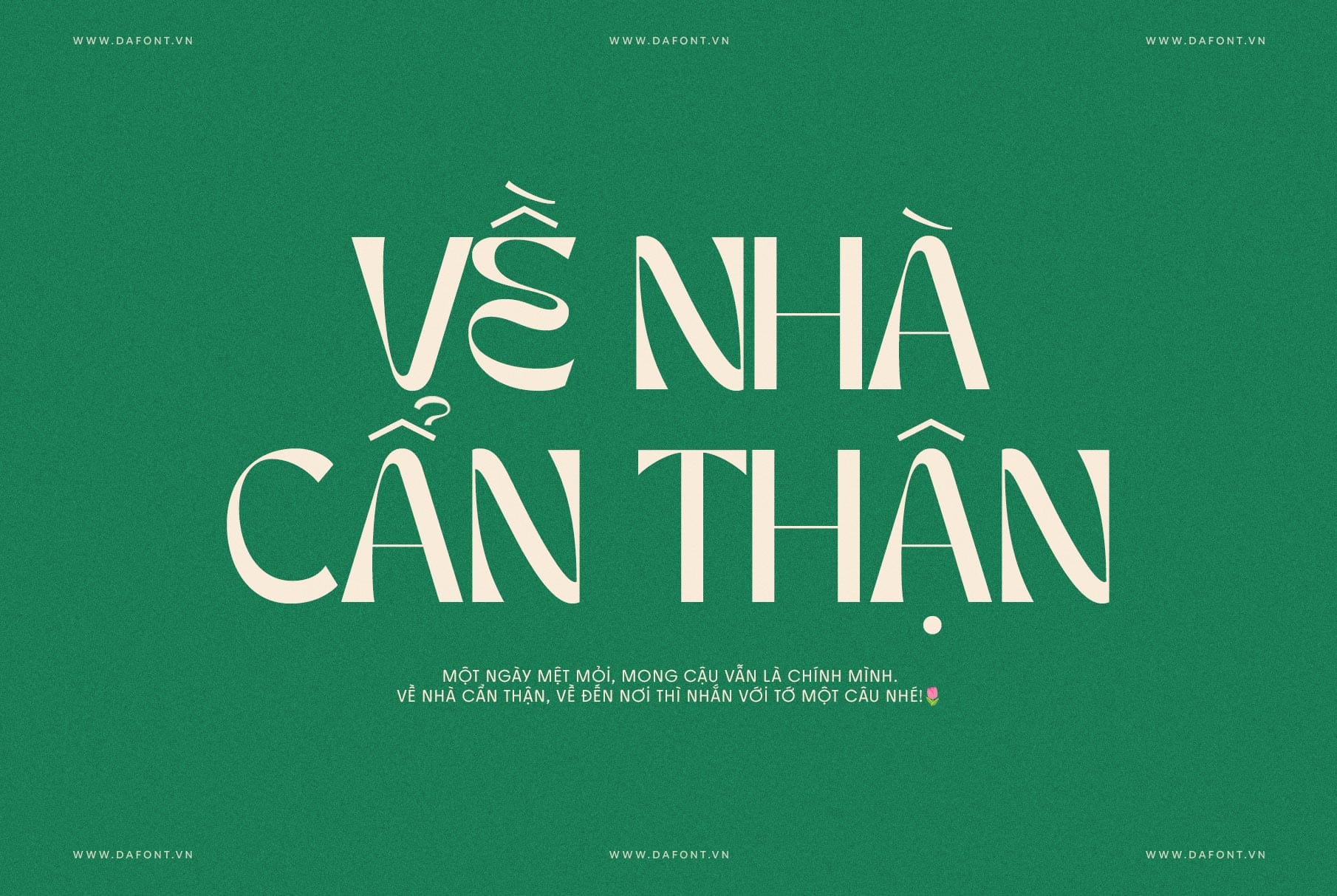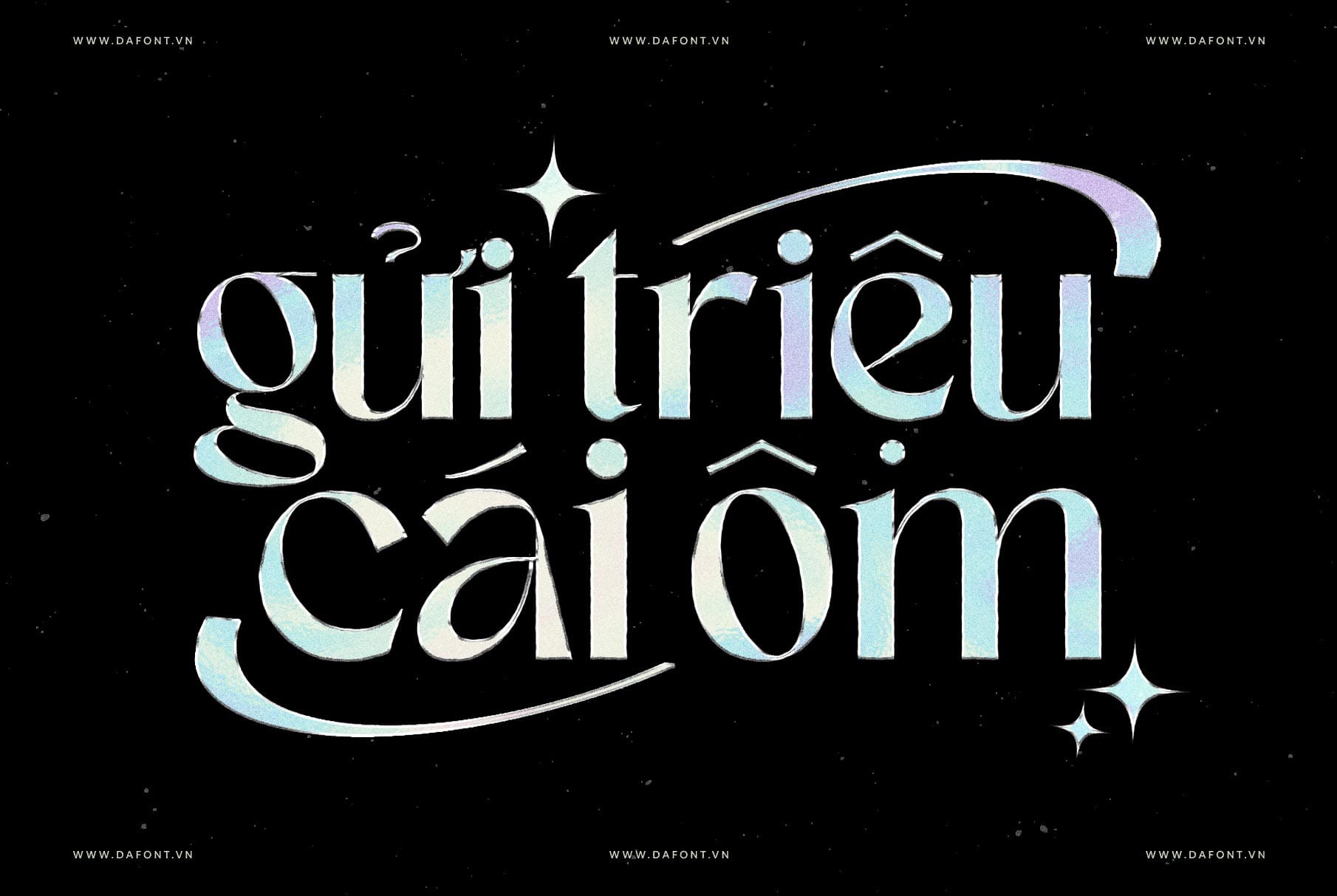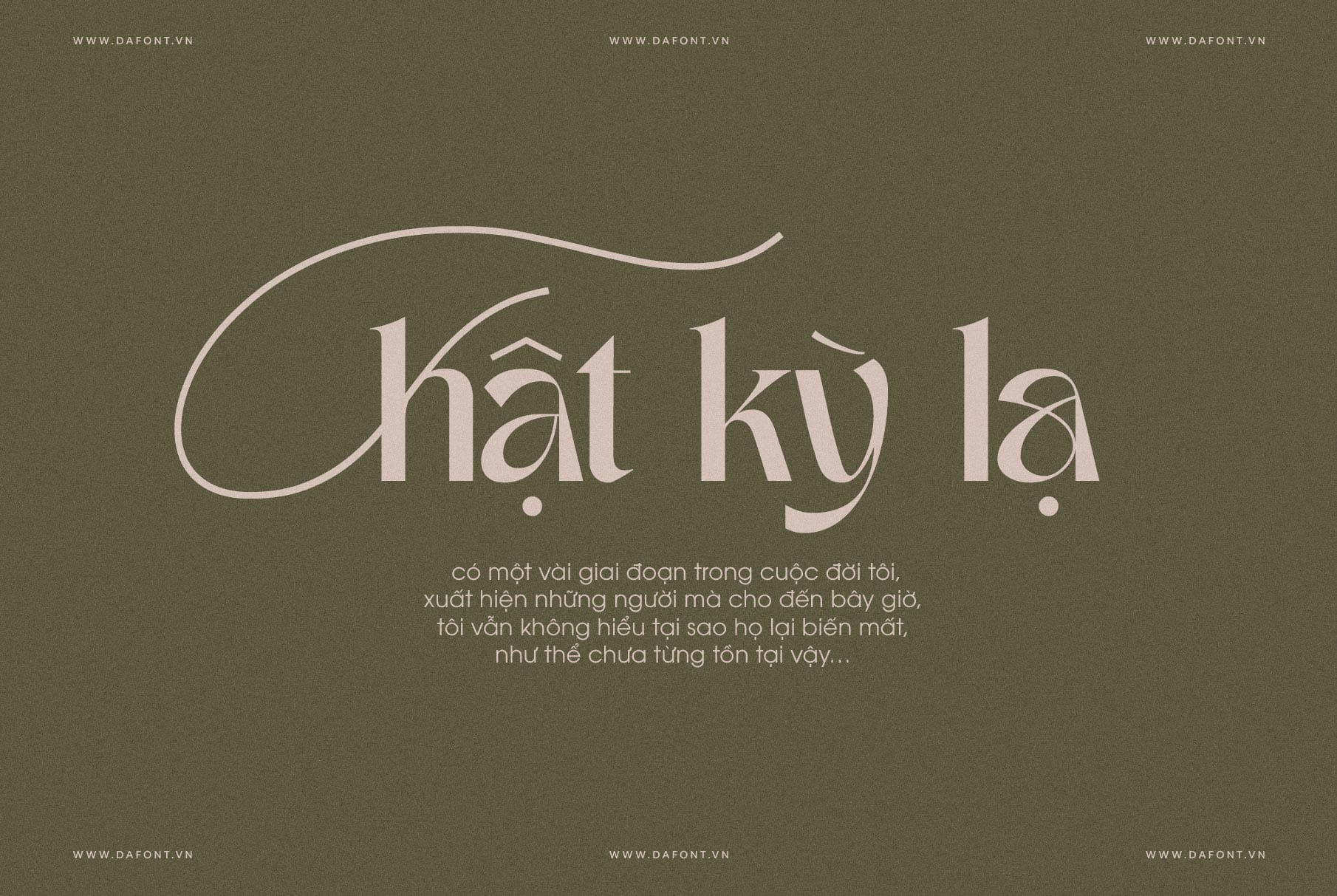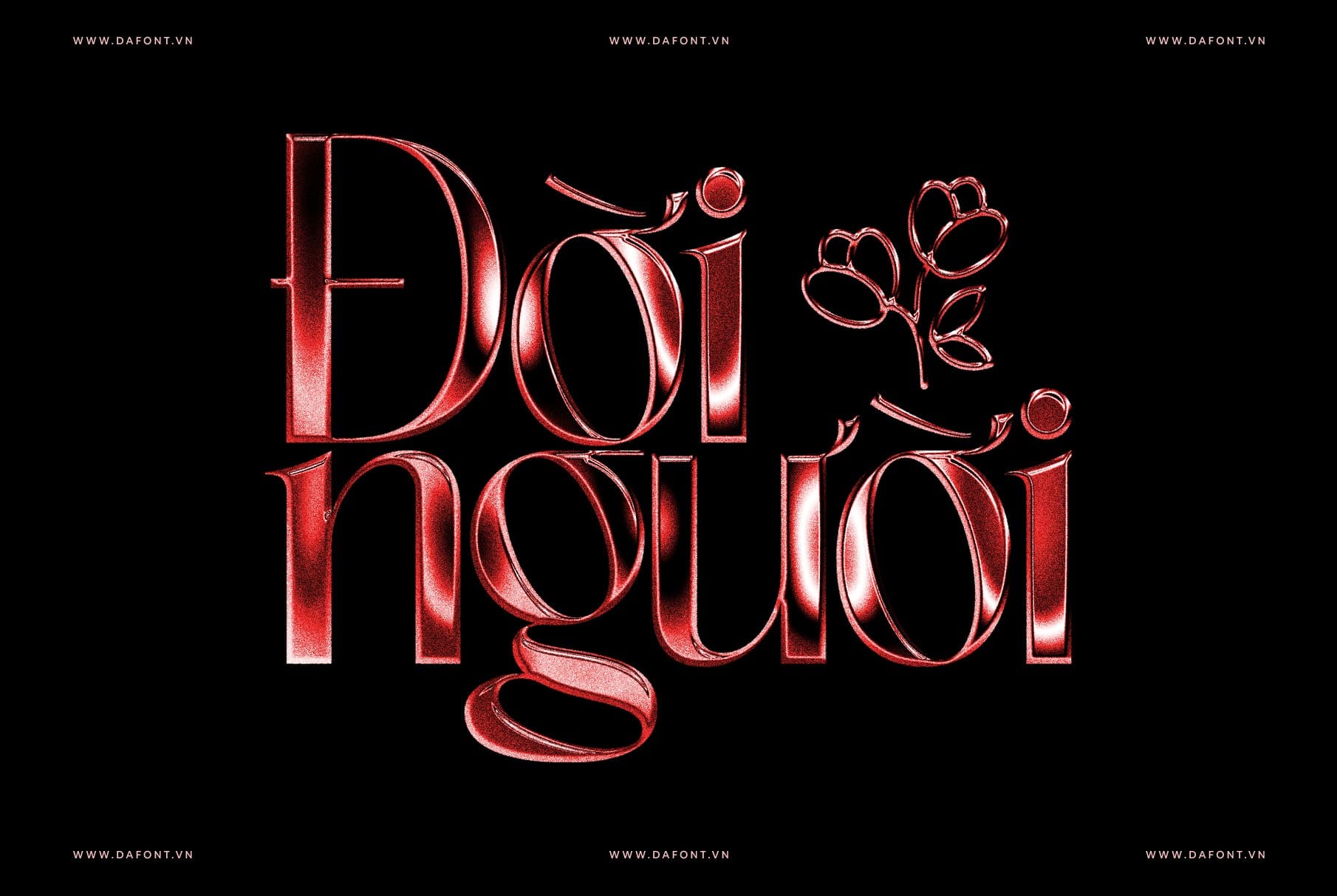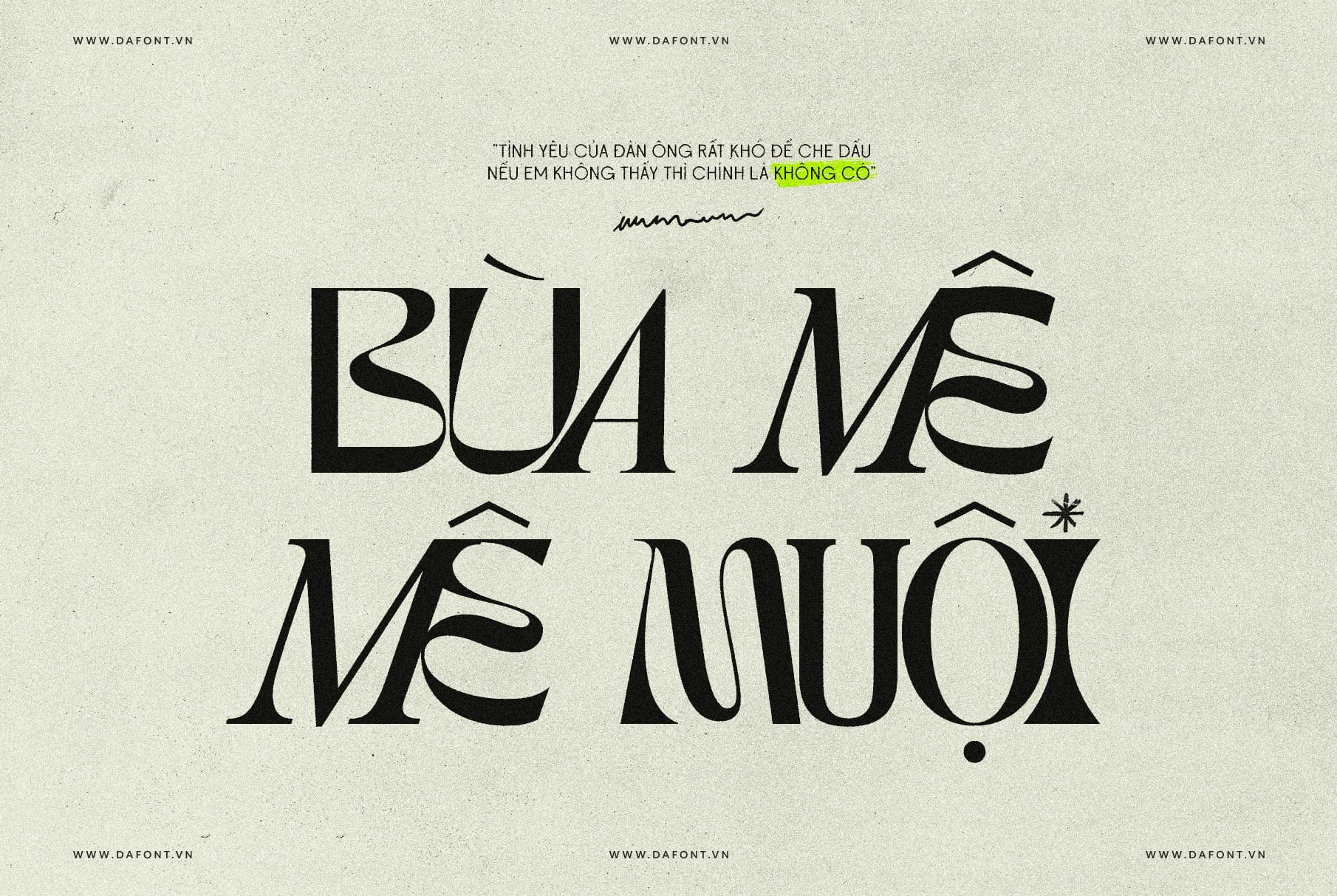
DFVN TAN – MERINGUE
Kiểu chữ retro hiện đại mang cá tính riêng
DFVN TAN – MERINGUE là một kiểu chữ hiển thị (display typeface) mang phong cách retro độc đáo, nổi bật với những đường cong mềm mại và đầy cá tính. Được thiết kế để mang lại sự vui tươi và nét riêng biệt, TAN – MERINGUE là lựa chọn lý tưởng cho những dự án cần sự sáng tạo và thu hút.
Điểm nổi bật DFVN TAN – MERINGUE
DFVN TAN – MERINGUE là một kiểu chữ hiển thị độc đáo mang phong cách retro, mang lại sự kết hợp hoàn hảo giữa tính hoài cổ và hiện đại. Đây là lựa chọn tuyệt vời cho những ai muốn thêm điểm nhấn cá tính vào các dự án thiết kế.
1. Phong cách retro: TAN – MERINGUE gợi nhớ đến những thiết kế cổ điển từ thế kỷ 20, kết hợp hoàn hảo giữa phong cách hoài cổ và hiện đại. Các đường nét mềm mại, uyển chuyển và tỉ mỉ khiến nó trở thành lựa chọn lý tưởng cho các thiết kế mang hơi hướng hoài niệm.
2. Đường cong ấn tượng: Những đường cong tinh tế của kiểu chữ này không chỉ tạo cảm giác mềm mại mà còn thêm phần thân thiện và gần gũi cho thiết kế.
3. Tính đa dụng: TAN – MERINGUE phù hợp với nhiều loại dự án như poster, bao bì sản phẩm, logo, thiết kế website, tạp chí, truyền thông xã hội và nhiều dự án thiết kế khác.
Ứng dụng của DFVN TAN – MERINGUE trong thiết kế
Nhờ sự độc đáo và linh hoạt, TAN – MERINGUE trở thành lựa chọn hàng đầu trong nhiều lĩnh vực thiết kế. Dưới đây là những ứng dụng tiêu biểu của kiểu chữ này:
1. Thiết kế thương hiệu:
TAN – MERINGUE với phong cách cổ điển pha chút hiện đại giúp tạo ra những logo độc đáo, thu hút và dễ nhận diện. Phù hợp cho các thương hiệu trong lĩnh vực thời trang, mỹ phẩm, hoặc thực phẩm.
2. Poster và Bao bì:
Kiểu chữ này là lựa chọn hoàn hảo để thiết kế các poster, bao bì, banner hoặc ấn phẩm quảng cáo. Các đường cong sinh động của TAN – MERINGUE dễ dàng thu hút ánh nhìn, đồng thời truyền tải thông điệp một cách rõ ràng và đầy cảm xúc.
3. Thiết kế đồ họa kỹ thuật số:
Trong các dự án thiết kế kỹ thuật số, DFVN TAN – MERINGUE có thể được sử dụng để tạo các yếu tố tiêu đề, trích dẫn hoặc làm điểm nhấn. Nó phù hợp với: Thiết kế bài đăng trên mạng xã hội (Instagram, Pinterest, Facebook, TikTok), bnner quảng cáo, typography trong video giới thiệu sản phẩm hoặc thương hiệu.
4. Thiết kế thiệp mời và ấn phẩm sự kiện:
Nếu bạn muốn các thiết kế thiệp mời hoặc ấn phẩm sự kiện của mình trông sang trọng và độc đáo, TAN – MERINGUE là một sự lựa chọn tuyệt vời. Các ứng dụng bao gồm: Thiệp cưới mang phong cách vintage, thiệp mời cho các sự kiện nghệ thuật, triển lãm, chương trình sự kiện với điểm nhấn về typography.
3. Thiết kế cá nhân hóa:
DFVN TAN – MERINGUE cũng phù hợp để tạo các thiết kế cá nhân, từ bộ chữ ký đến các sản phẩm như: Lịch để bàn hoặc treo tường, bookmark (dấu trang) theo phong cách riêng, trang trí hoặc quà tặng cá nhân.
Tại sao nên chọn DFVN TAN – MERINGUE?
Kiểu chữ này mang đến cho dự án của bạn một phong cách riêng, khó nhầm lẫn. Nếu bạn đang tìm kiếm một kiểu chữ hiển thị Việt hóa vừa mang nét hoài cổ, vừa hiện đại và sáng tạo, DFVN TAN – MERINGUE chính là sự lựa chọn hoàn hảo.
Font được DFVN Việt hóa, chỉnh sửa, kerning lại, tối ưu và các dấu được căn chỉnh 1 cách cẩn thận. Ngoài ra, 1 số ký tự thay thế như chữ E và a được Việt hóa đầy đủ dễ dàng sử dụng bằng tính năng Opentype.